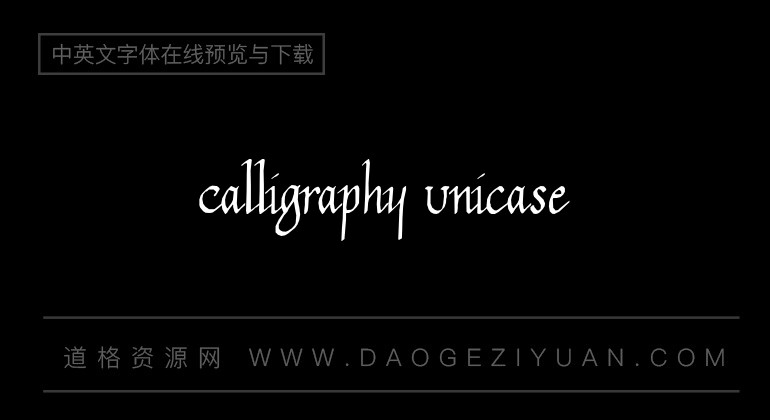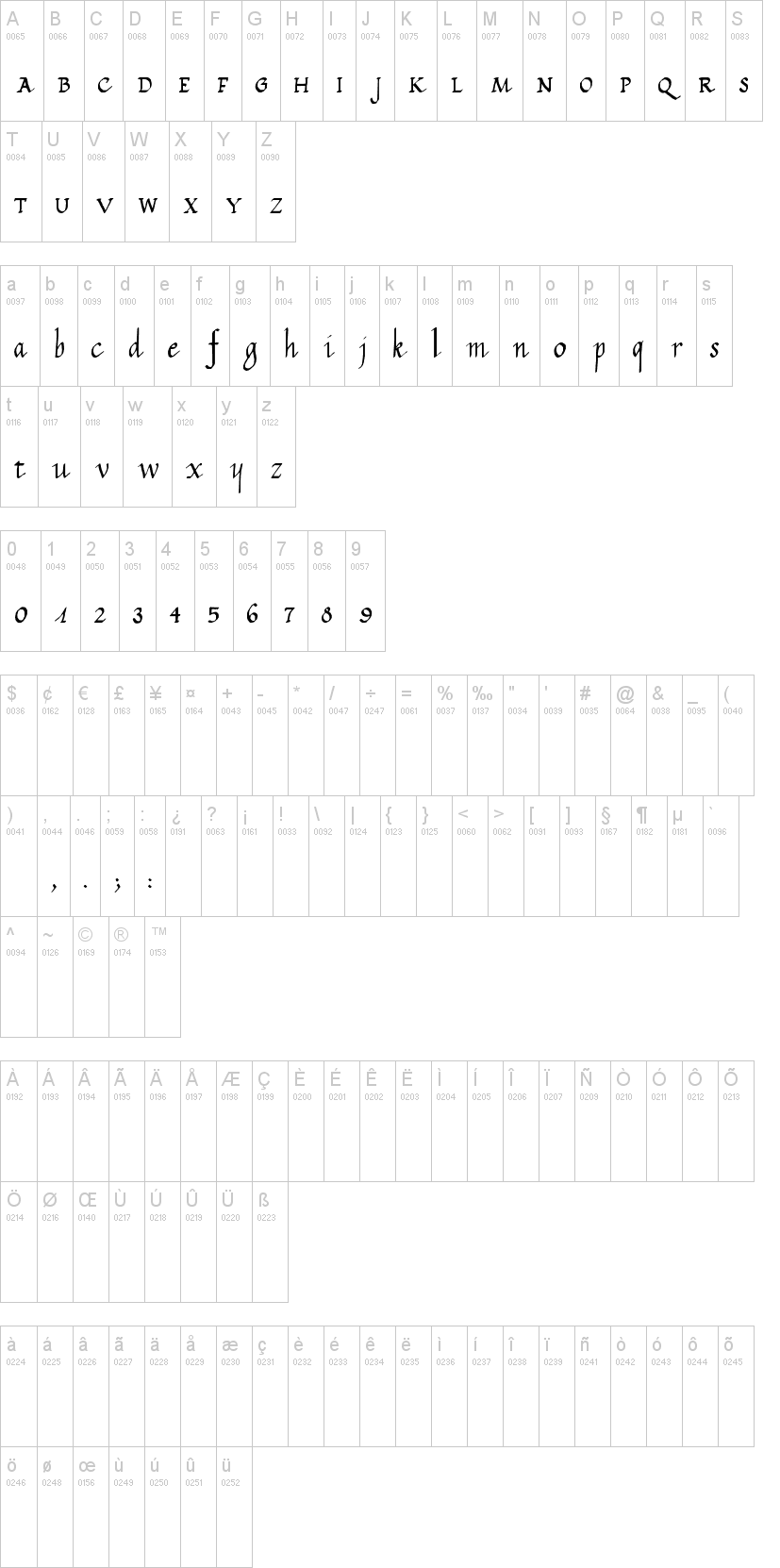
Calligraphy Unicase
Calligraphy Unicase 字体是一款结合了钢笔书法和大写字母的字体,它独特的外观和手感能够为文字提供一种充满艺术感的效果。它的字形精细细腻,笔画流畅美观,有着让人惊叹的视觉效果。它的字形设计精致,可以用于各种文字类型,可以在印刷品、网页、图形设计等方面使用,可以给您的文字带来更加精致的质感和外观。
Calligraphy Unicase是一款非常不错的手写艺术字体,具有很好的视觉感,适合于文化类的宣传设计、商业类品牌的广告和产品包装设计以及个性化文字排版等较多场景。
Calligraphy Unicase字符映射图